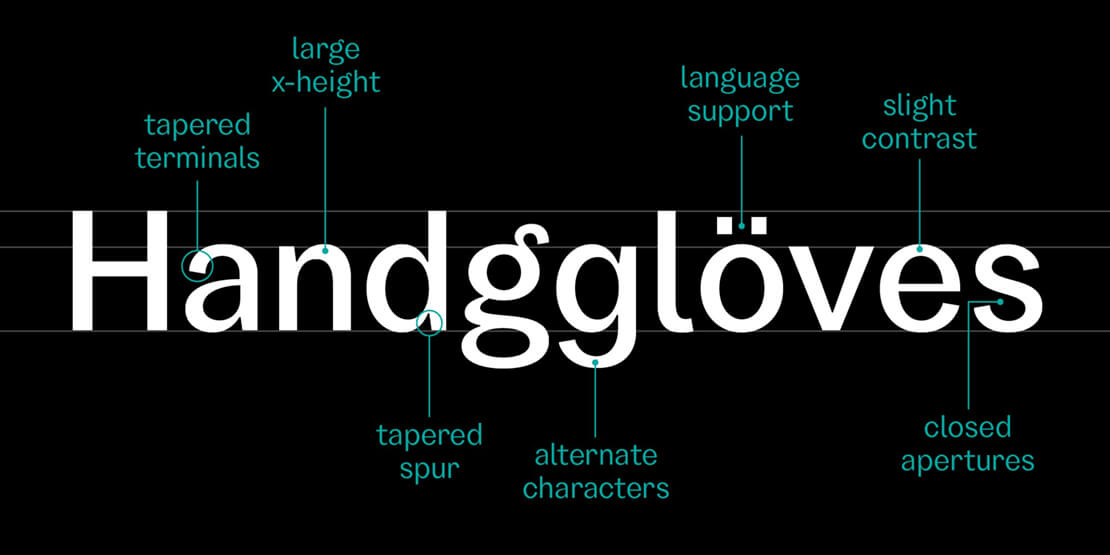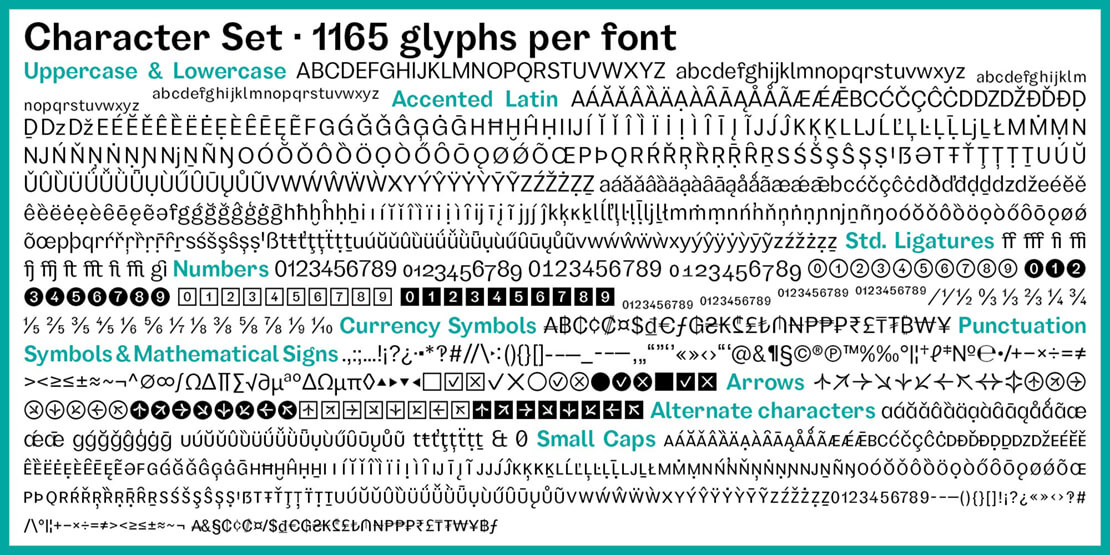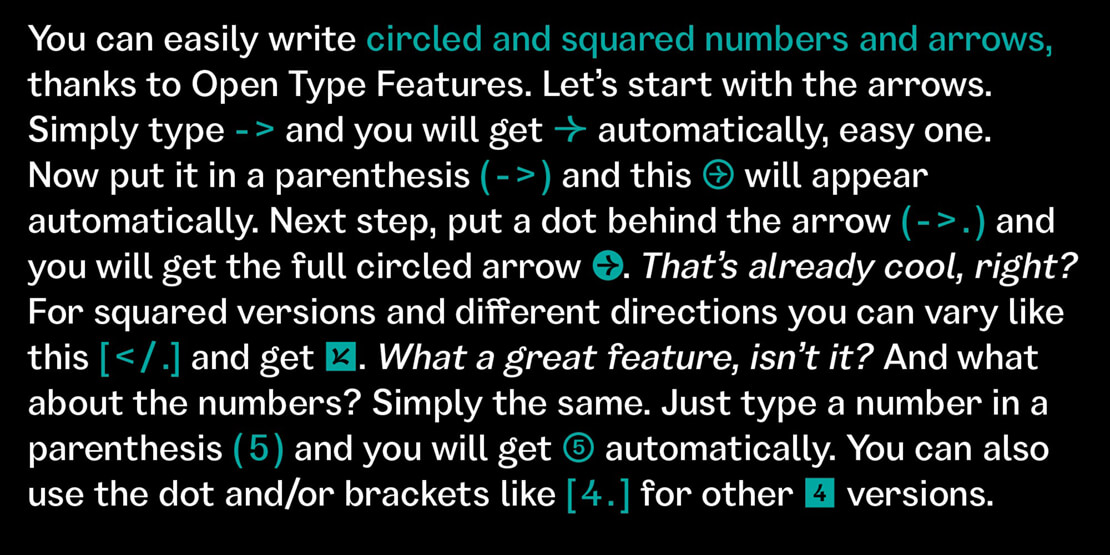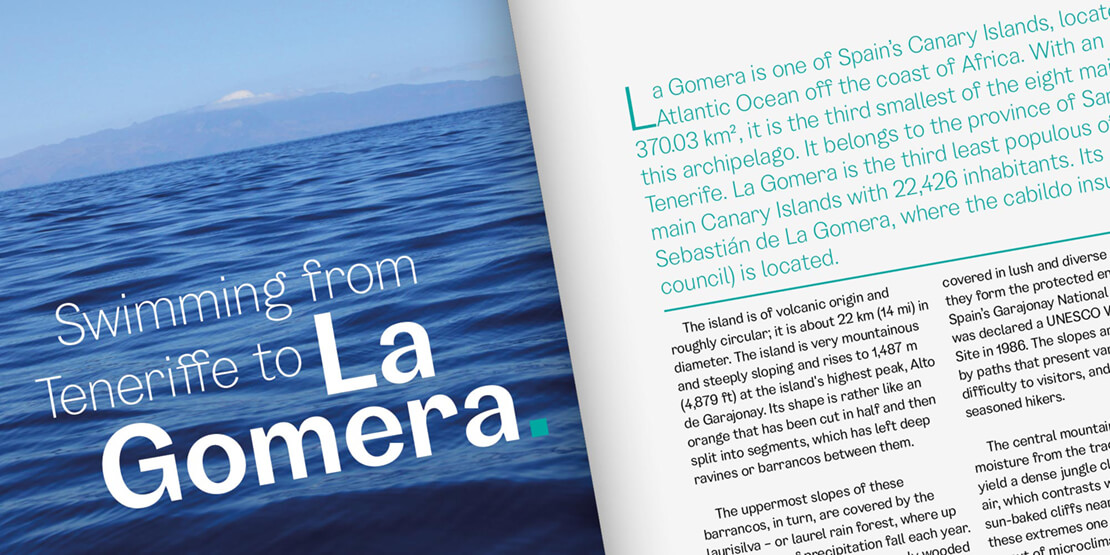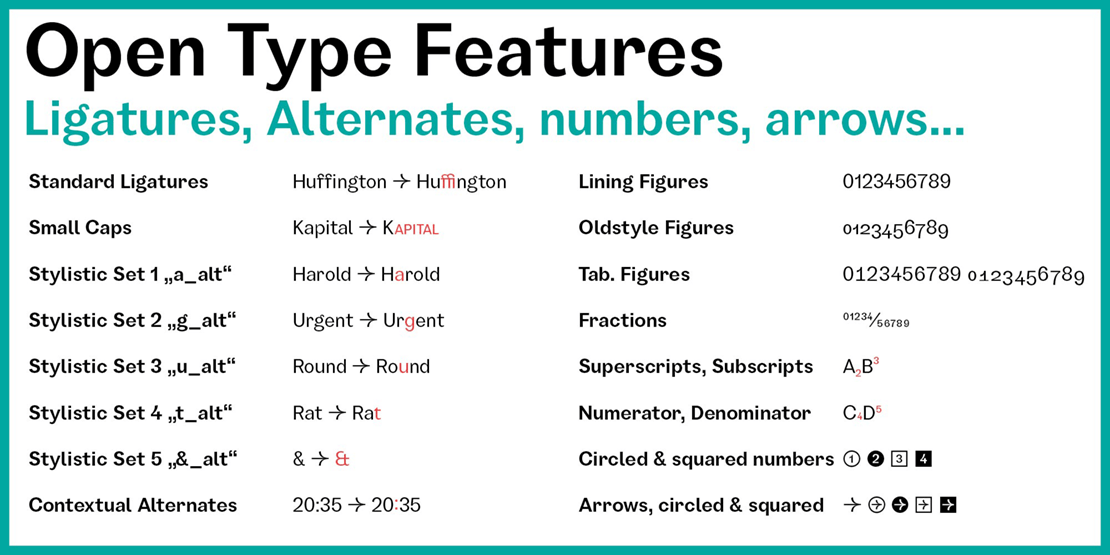
Garino: Moderne Sans-Serif-Schriftfamilie
Type-Designer Julien Fincker präsentiert seine neue Schriftfamilie. »Garino« bietet einen dynamischen Schwung in den Kurven und kontrastreiche Übergänge.
Die dünneren und dickeren Gewichte sollen sich insbesondere für starke Headlines eignen, während die mittleren Gewichte eher für typographische Herausforderungen und Fließtexte geschaffen sind. Daher lässt sich die Schrift sowohl zurückhaltend als auch expressiv einsetzen.
»Ein vielseitiger Allrounder, der allen Herausforderungen gewachsen ist – für Corporate Identity, Editorial, Branding, Orientierung- und Leitsysteme und vieles mehr.«, so Julien Fincker über seine neue Schriftfamilie.
»Garino« verfügt über insgesamt 20 Schnitte (von »Thin« bis »Heavy«) sowie entsprechende kursive Varianten. Mit über 1.165 Zeichen deckt sie mehr als 200 lateinbasierte Sprachen ab und verfügt dabei über eine Vielzahl an Währungszeichen und eine ganze Reihe Open Type Features. Es gibt alternative Zeichen als Stylistic-Sets, Small Caps, automatische Brüche und vieles mehr.
Ein besonderes Augenmerk hat Julien Fincker zudem auf die umfangreiche Auswahl an Pfeilen und Nummern gelegt. Durch Opentype-Features und einer einfachen Systematik lassen sich die entsprechenden Ausführungen auch einfach direkt »schreiben«, ohne sie zuvor in einer Glyphen-Palette auswählen zu müssen.